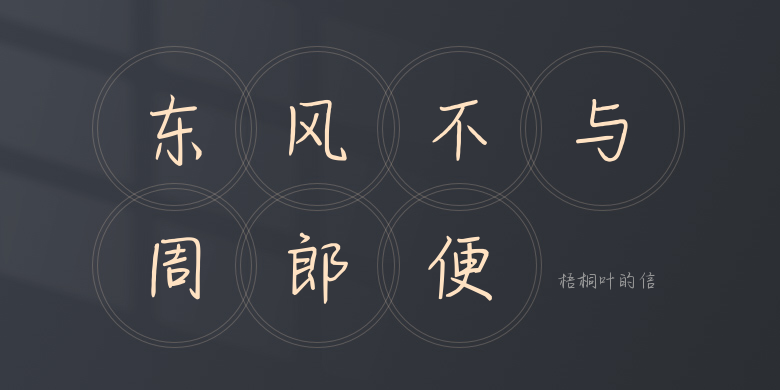
梧桐叶的信
梧桐叶的信,这款字体结构工整、笔画清晰,兼顾美观与易读性,适用于标题、正文、海报、包装、LOGO 等多种场景。字形优雅稳定,风格百搭耐看,适配日常排版与创意设计,让文字呈现更舒适、更具质感。梧桐叶的信一笔一画,皆是细节,以均衡的比例、流畅的线条打造舒适视觉体验,字形端正大气,风格简约现代。无论是商业设计、品牌宣传还是日常排版,都能轻松驾驭,让文字更有格调与力量。梧桐叶的信字体下载。